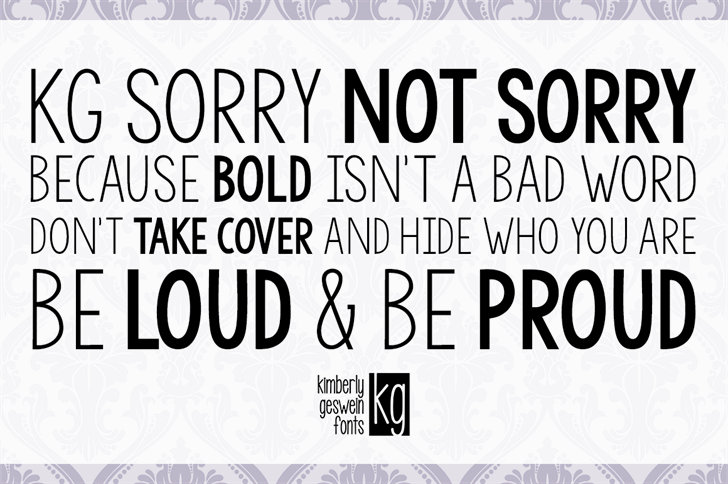
A fonte KG Sorry Not Sorry é uma criação moderna que traz elementos retro e elegantes para qualquer projeto digital. Lançada pela designer Kimberly Geswein em 2015, esta fonte adota um estilo nostálgico sem deixar de ser contemporâneo. Ideal para aqueles projetos que buscam um equilíbrio perfeito entre o clássico e a criatividade moderna, a KG Sorry Not Sorry oferece uma mistura única de caracteres familiares e arredondados, com um toque interessante de contraste. Perfeita tanto para fontes de texto quanto para legenda em imagens, esta fonte é perfeitamente adaptada para categorias como Retro Fonts, tornando-a uma escolha inteligente para designers que buscam uma fonte vintage e versátil sem deixar de lado o conforto do estilo moderno.